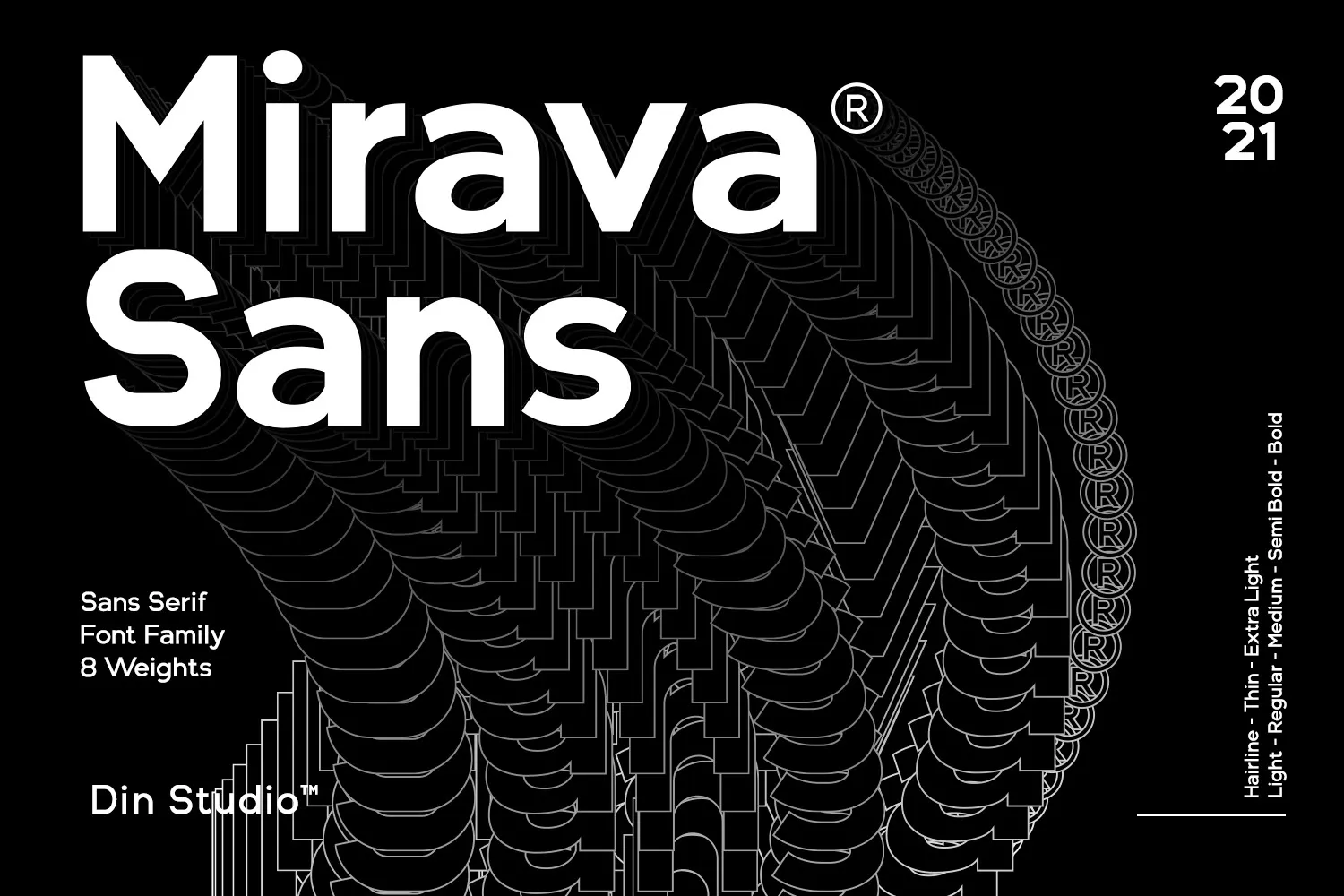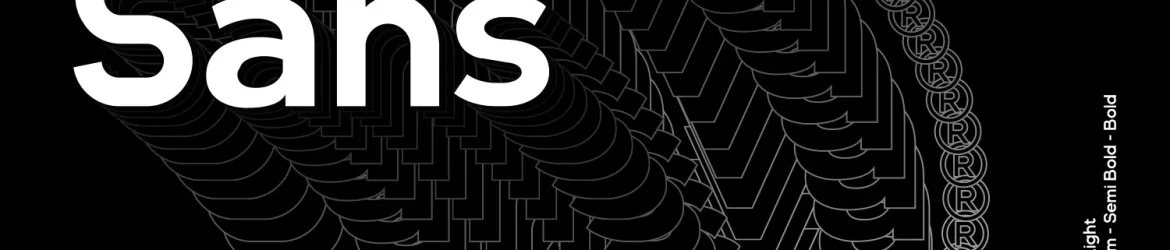
Mirava Font – Download Grátis
Esta é uma nova grotesca inspirada nos tipos de fachada suíços dos anos 1950. Com esta família de letras, você terá muitas opções para maximizar suas criações com tipos estilizados. Esta font foi projetada para dar vida à sua marca e adicionar um toque moderno, divertido e elegante. Mirava abraça a oportunidade de escrever o conteúdo que precisa enviar aos seus leitores. É perfeito para criar marcas inovadores, logotipos, menus, gráficos em mídias sociais e muito mais. O design da fonte Mirava é uma ótima escolha para designers em constante busca por estilos modernos e criativos que possam se adaptar a diversos projetos. Suas linhas clean e simples tornam-na um recurso versátil para criar visualmente impactantes e comunicativas, sem perder sua elegância e simplicidade. Quebre as regras com Mirava, ou mesmo apenas dê um passo à frente na forma como você aborda seu próximo design.